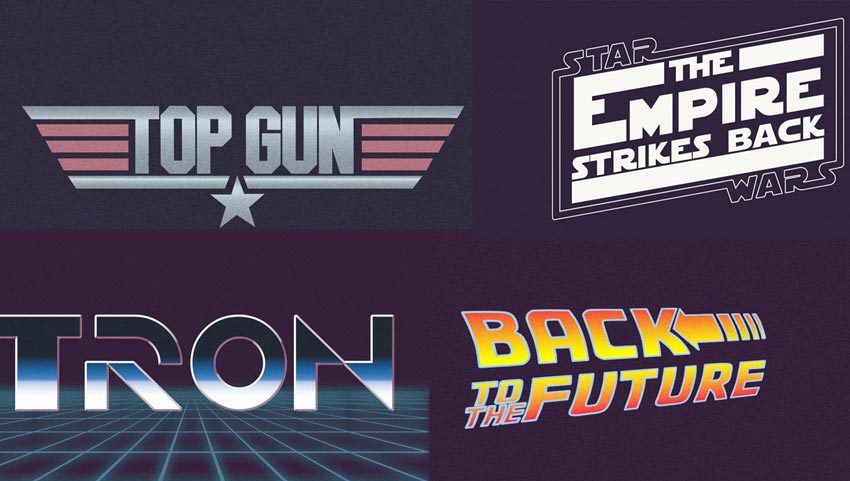
Teoría tipográfica
abro éste hilo para compartir información sobre tipografía, sus usos, características, historia e información general.
Tipografía de los 80´s: Si quieres saber más detalles sobre el periodo retro de los 80:
Te la recomiendo porque se centra sobretodo en la teoría tipográfica (espaciado, clasificación, vocabulario, etc.).
He estado echando un vistazo a tu blog, y he encontrado buen material. Me ha encantado este jueguecito de kerning. :)
Gracias Capitán América. Opino lo mismo que tú. En este país la Tipo es como si no existiera. Hasta en los planes de estudio (por lo menos en la pública) son ridículos. Ahora hay un grupo de gente (Lletraferits) que estamos intentando ponerle coto y solución a este problema. Si tienes alguna duda o sugerencia no dudes en contactar.
la tipografía es el patito feo de muchas agencias.
Como diseñador me doy cuenta que apenas sé nada sobre la materia,
aunque me he ganado la vida tranquilamente sin que nadie me llamara la atención nunca al respecto.
Cuando visité una multinacional en londres (Saatchi), además de redactor, director de arte y head of art, existe la figura del tipógrafo, una perosna que no sólo selecciona la fuente para del anuncio, si no que en algunos casos hasta la diseña "ad-hoc".
Así les va de bien a los creatas anglos.
Tengo que ponerme las pilas y autoformarme en mi tiempo libre.
Engel Light ltd.
Me gusta, pero no sé en que eentorno podría utilizarla.
¿Un flyer modernuki?
¿Un catálogo ultra limpio y pulcro?
aquí va otro portal, en donde se experimenta bastante con la tipografía, y ofrecen buenas tipos para descargar gratis, especial atencion a la <em>Engel Light ltd</em>
Descubrí la Montag ayer (creo que bebemos de los mismos manantiales), y tengo muchas ganas de probarla en un par de cosas que tengo en la cabeza :)
interesantes tipos: